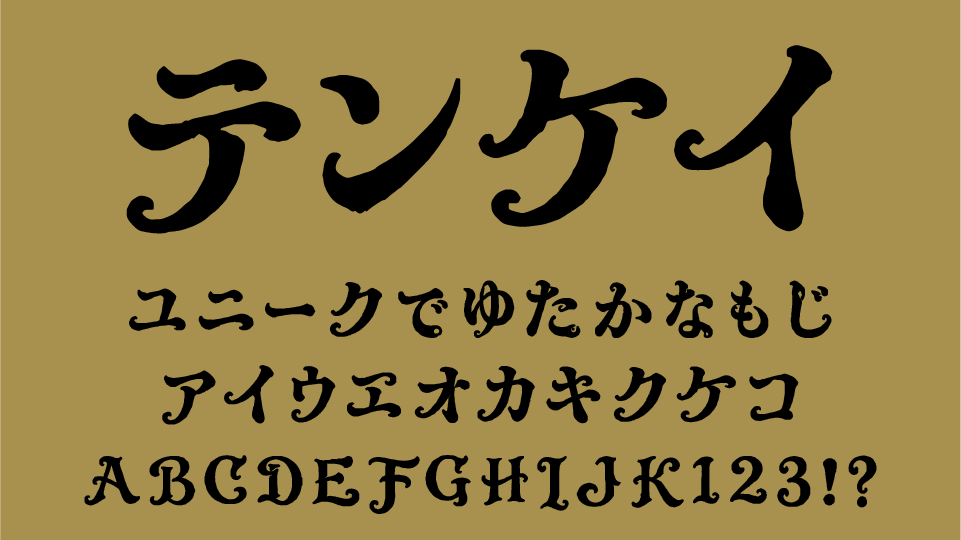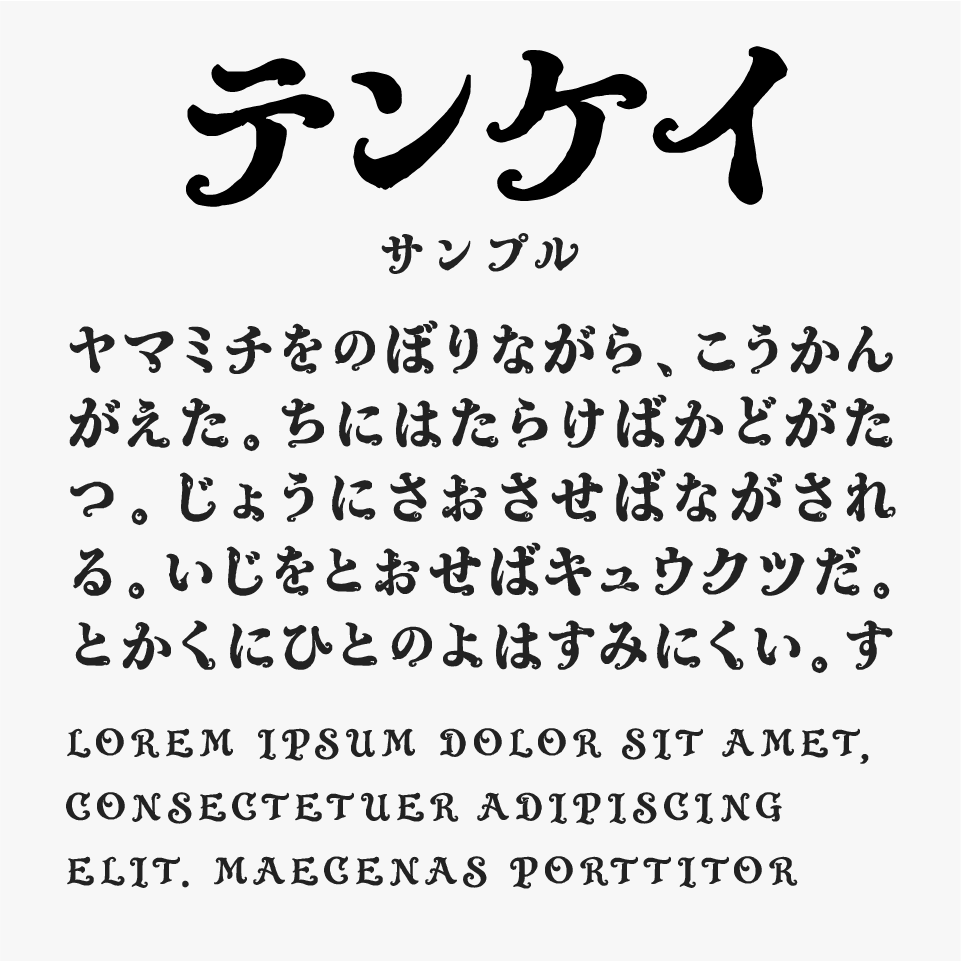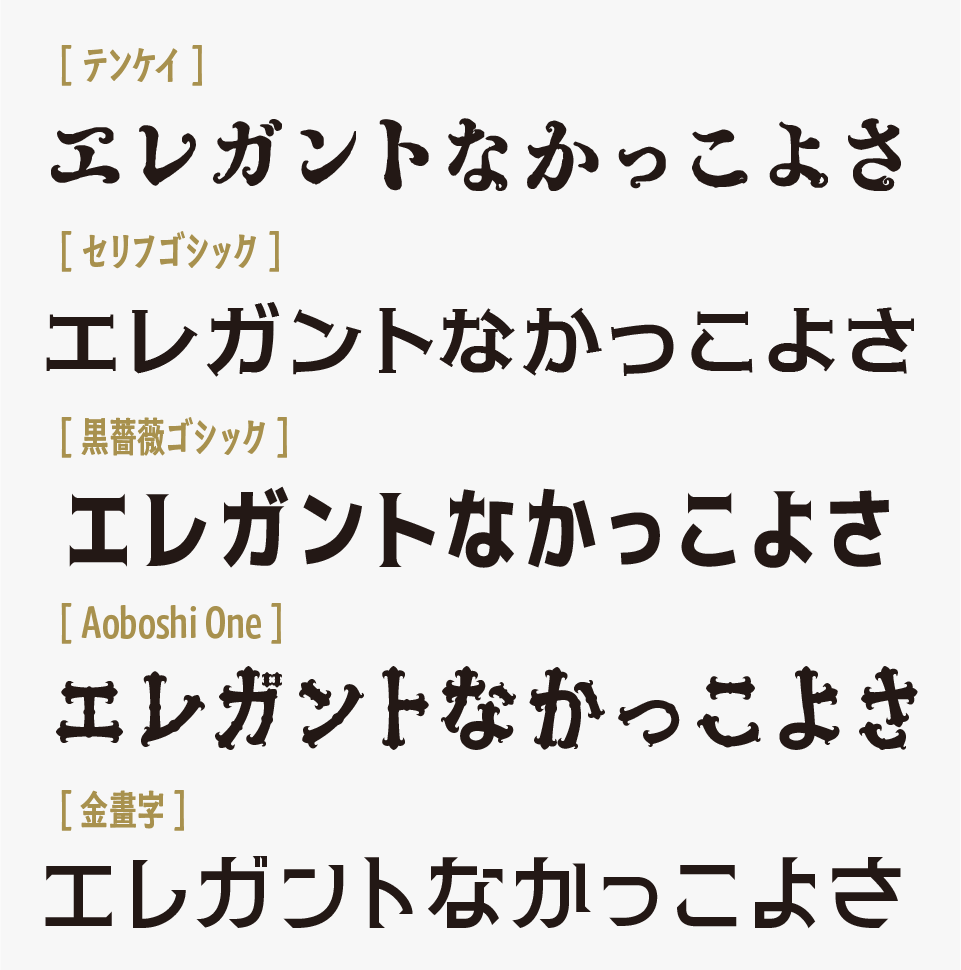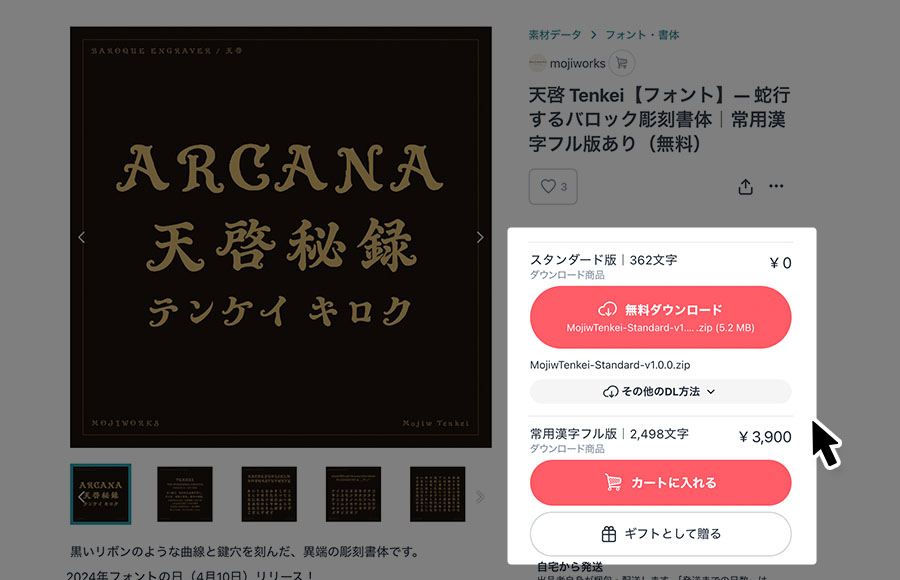
天啓(テンケイ)
天啓(テンケイ)フォントは、明朝体をベースにしながら、文字の先端に大きく渦を巻くような装飾を施した個性的なデザインフォントです。
クラシカルな骨格と大胆な装飾が組み合わさることで、アンティークやヨーロッパの古い装飾文字を思わせる高級感が感じられるフォントです。優雅で存在感がありながらも可読性を保っており、タイトルやロゴで華やかな印象を与えてくれるフォントです。
ファンタジー作品やアンティークデザイン、洋館、紅茶、お菓子のパッケージ、イベントタイトルなどにぴったりなフォントです。上品さと装飾性を兼ね備えた雰囲気が作品全体の世界観を引き立て、特別感や気品を演出したい場面で活躍してくれるフォントです。
天啓(テンケイ)フォントを、ほかのクラシカルでかっこいいフォントと比較してみると、 文字の存在感がしっかりとしており、格式高い印象と力強さが感じられるフォントです。
比較フォントは、「セリフゴシック」「黒薔薇ゴシック」「Aoboshi One」「金畫字(キンカクジ)」と使用していますが、どれも特徴的な明朝体フォントなので、ぜひあわせてチェックしてみてください。